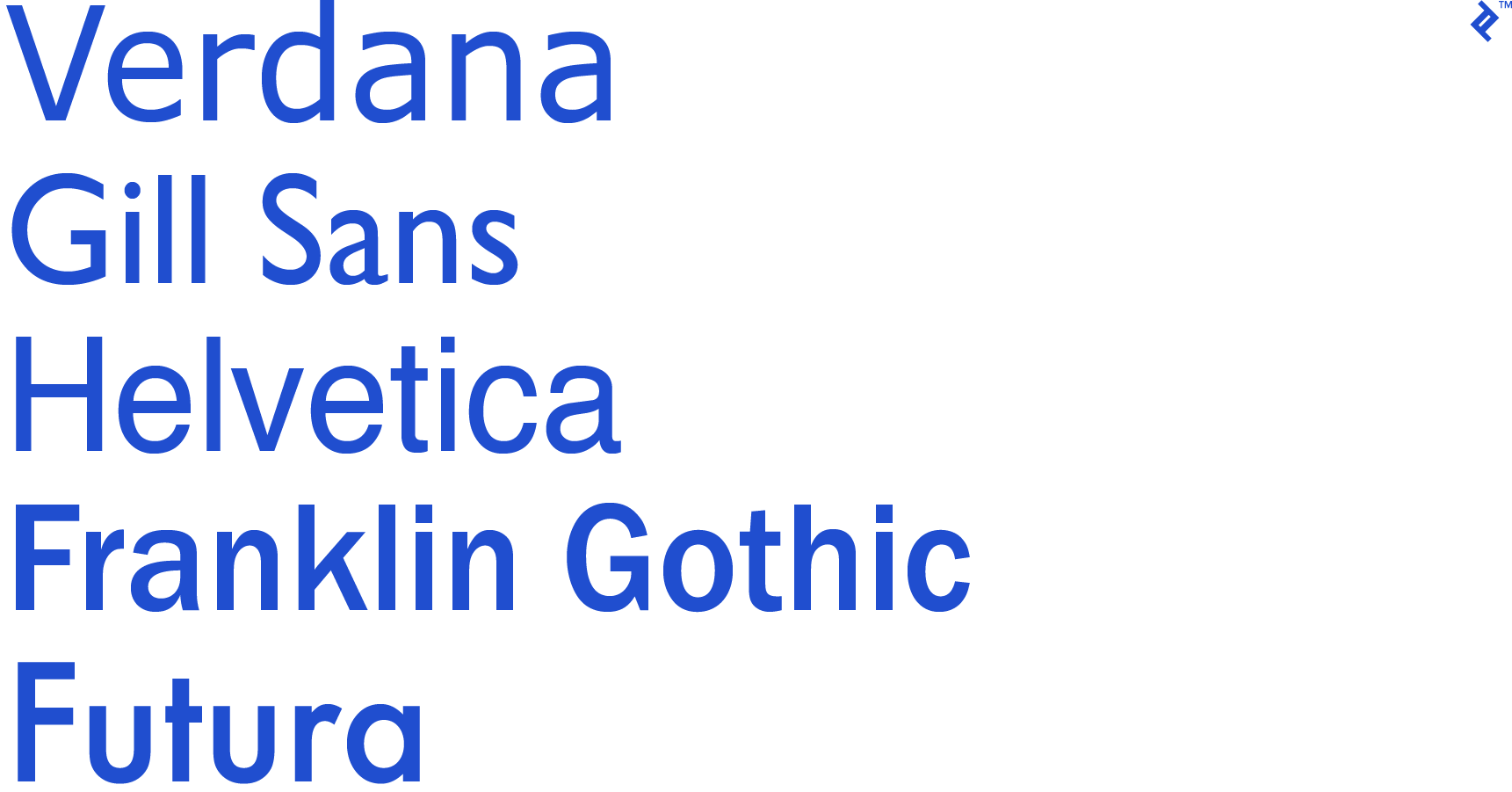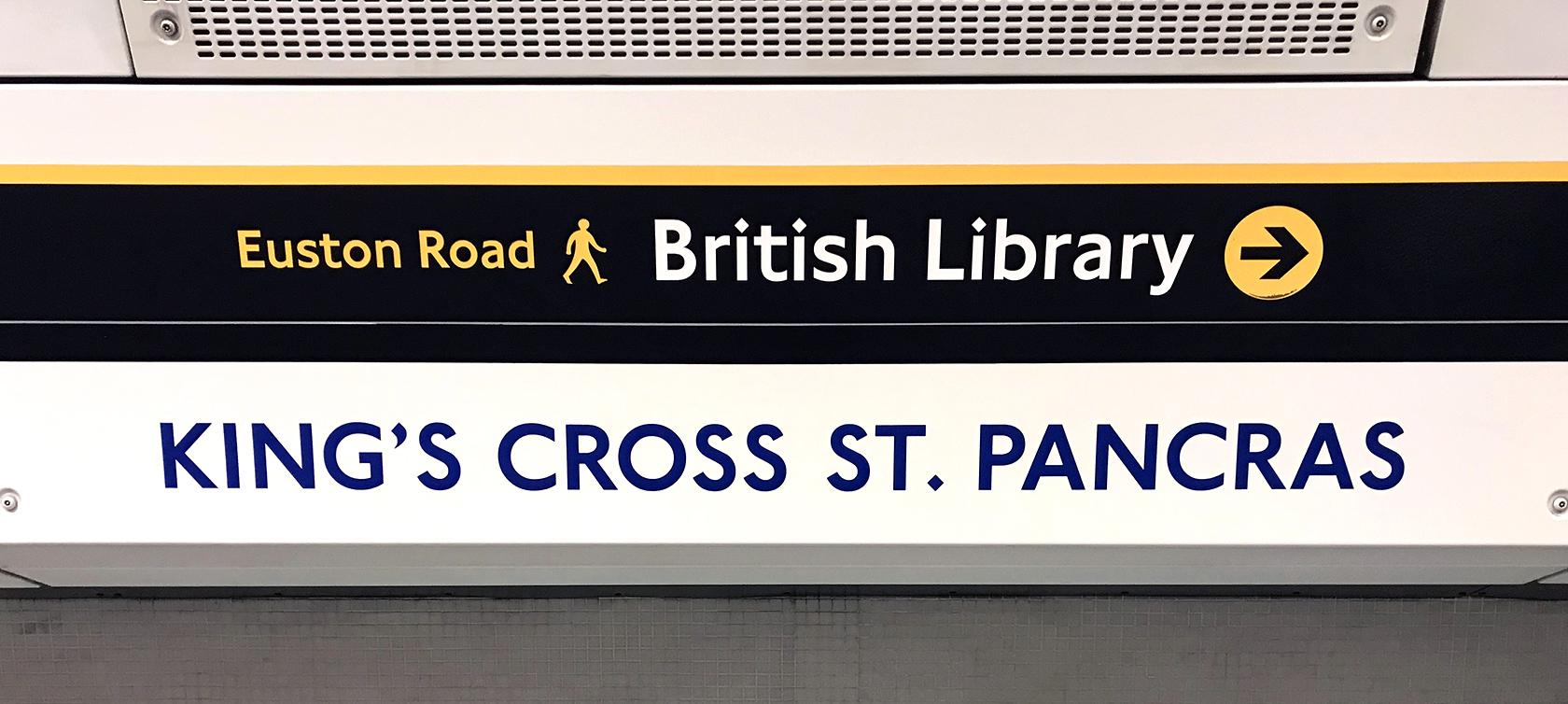
Estilos de Tipografía para la Web y Diseño Editorial e Impreso
Independientemente de la disciplina de diseño en la que estés trabajando, ya sea el diseño visual, UX o los tipos de tipografía tradicionales, son elementos esenciales de casi todo el diseño que se produce.
La gran mayoría de las personas son bombardeadas con tipos de letra desde el momento en que se despiertan por la mañana hasta el momento en que se van a la cama por la noche. Desde las aplicaciones en sus teléfonos hasta los productos de arreglo personal en sus baños hasta los letreros que ven en sus viajes diarios a la mañana, la tipografía está en todas partes. Pero ¿cuántas personas realmente notan los estilos tipográficos que rodean todos los días?
Incluso los diseñadores subestiman los estilos de tipografías y, a menudo, toman decisiones de tipografías basadas en una opinión vaga en lugar de una comprensión objetiva. ¿La mayoría de los diseñadores siquiera conocen los contextos industriales originales para los cuales se diseñaron varios tipos de letra? ¿Qué significan estos contextos e historias para determinar la legibilidad, el carácter apropiado y el uso de un tipo de letra dado? No importa en qué disciplina de diseño se esté trabajando, ya sea diseño visual o UX o tradicional diseño de impresión, los estilos de tipografía son elementos esenciales de prácticamente todo el diseño producido.
Algunos de los tipos de letra más influyentes actualmente en uso a menudo se pasan por alto a favor de diseños de tipografía únicos que son más nuevos en el mercado, y a veces con razón. Cada uno de los tipos de letra en este artículo tiene décadas, si no siglos, y fueron diseñados para diferentes contextos tecnológicos. Por lo tanto, se han creado muchas alternativas o actualizaciones desde que se introdujeron. Incluso algunas de las fuentes originalmente diseñadas para pantallas se han quedado obsoletas ya que las pantallas e impresoras se vuelven de mayor resolución y son capaces de mostrar formas más complejas con precisión.
Tipografías Serif
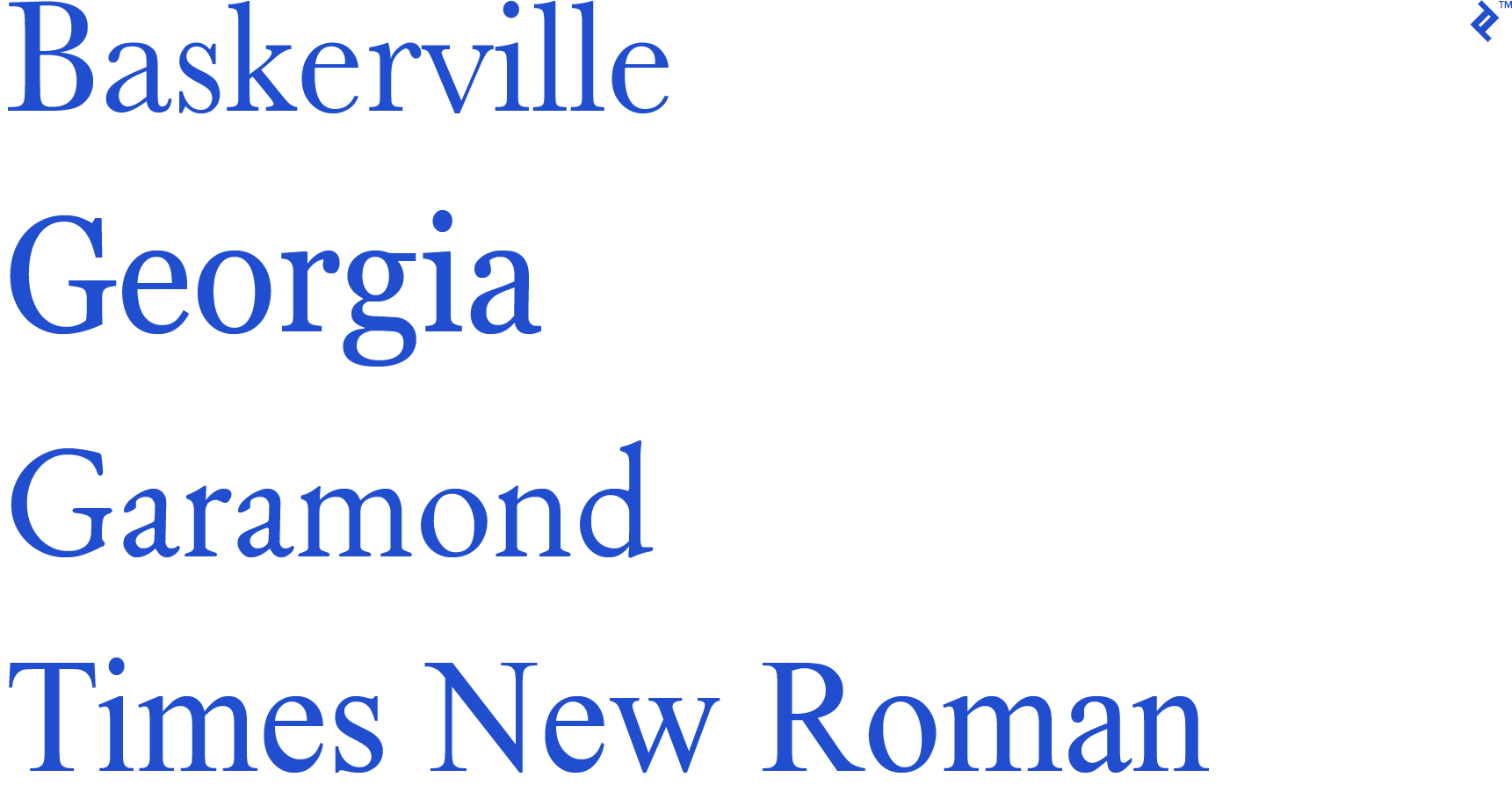
Comprender la diferencia entre los estilos de letra serif y sans-serif es una de las reglas de tipo más fundamentales. Para muchos esto puede ser obvio, pero el serif es el trazo dado al final de las principales líneas horizontales y verticales de un caracter. Hay muchas subclases dentro de serifs, incluyendo rayitas, cuñas y serifas de losas, que describen las cualidades visuales del serif.
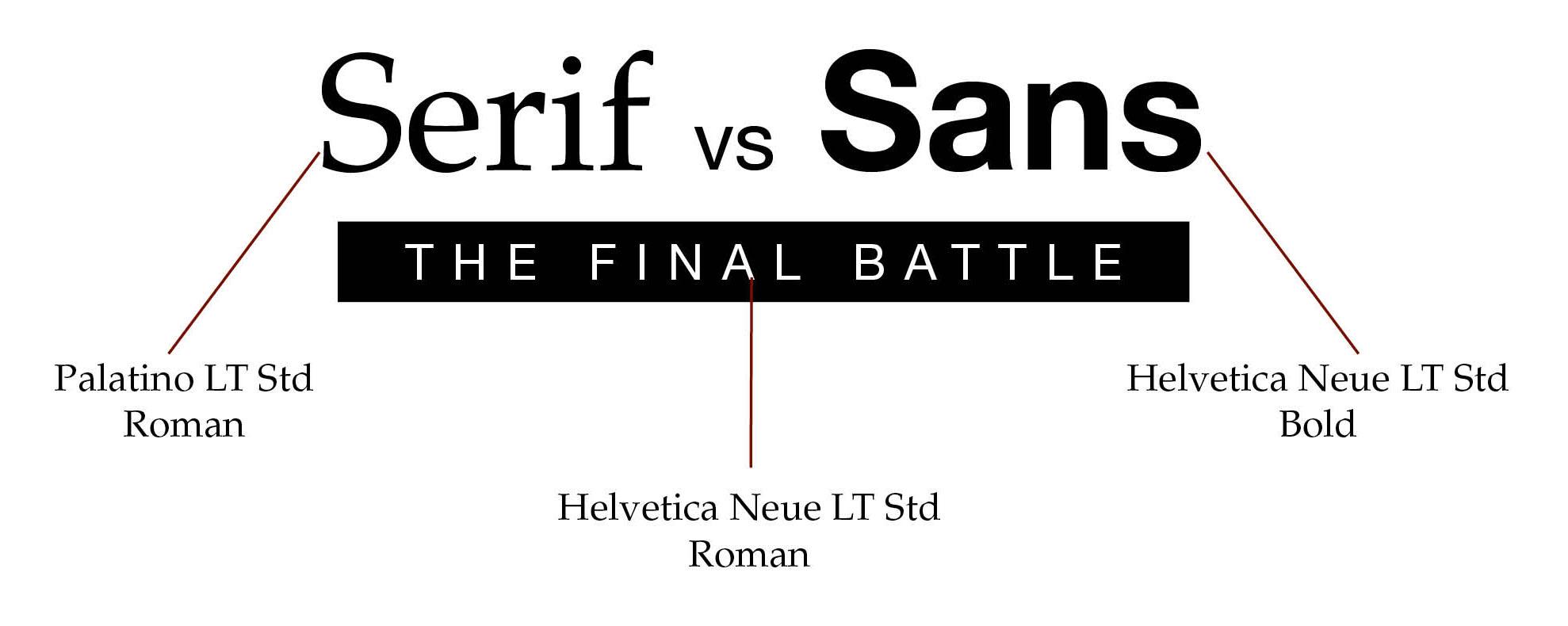
En general, las serifas tienen una historia más larga que las san serifs, ya que fueron las primeras tipografías usadas para imprimir libros después de la invención de Gutenberg Press. Esencialmente, las serifas permiten una lectura más cómoda en detalle, ya que las serifas guían el ojo suavemente de un personaje a otro, por lo que el serif es ideal para trabajos impresos largos. Debido a esto, las serifas aún son generalmente la fuente de referencia para trabajos impresos, como libros o informes, aunque no es una regla absoluta. Cada tipo de letra tiene sus propias cualidades específicas, y hay algunos tipos de letra serif que no son realmente adecuados para grandes fragmentos de texto corporal (y algunos tipos de letra sans-serif que son perfectamente legibles y legibles para trabajos largos).
Baskerville
Baskerville es una de las serifas clásicas que ha resistido la prueba del tiempo y todavía se usa ampliamente hoy en día. Baskerville fue diseñada en un período de transición entre las primeras caras tipográficas (Bodoni y Didot) y los tipos de letra de los siglos XIX y XX por venir. Baskerville ha tenido éxito debido a sus formas de letras de alto contraste.
El diseñador, John Baskerville, era un perfeccionista intenso y creó una fuente con hermosos detalles. El tipo de letra solo se puede imprimir en sus propias máquinas para garantizar que las formas de letras se transfieran correctamente a la página. Esta historia es significativa, ya que Baskerville se ha adaptado a los diversos medios en los que trabajamos hoy. Los detalles incorporados en cada forma de letra hacen que Baskerville no sea adecuado para medios de baja resolución, incluidas pantallas de baja resolución o impresoras defectuosas. Dicho esto, cuando Baskerville tiene la oportunidad de expresar su calidad, es una excelente tipografía serif.
Un buen ejemplo de una tipografía digital moderna en la que Baskerville ha influenciado mucho es la tipografía que Amazon ha encargado para Kindle, Bookerly. Si estás buscando una alternativa a Baskerville que mantenga su riqueza de 200 años mientras se actualiza para ser legible en la pantalla, Bookerly podría ser una buena solución. Otras alternativas incluyen Sra. Eaves y Plantin.
Times New Roman
Times New Roman, al igual que muchas fuentes ampliamente utilizadas desde hace un tiempo, es una tipografía polarizante que es amada por muchos pero también es detestada por algunos. A menudo, lo que las personas aman u odian sobre TNR es lo mismo: su neutralidad apática.
Matthew Butterick escribe “Times New Roman no es una elección de letra, sino la ausencia de una elección de fuente, como la negrura del espacio profundo no es un color. Mirar Times New Roman es contemplar el vacío”. Times New Roman se siente tan claro en gran parte debido a su abrumadora ubicuidad como resultado de su exposición del periódico para el que fue diseñado, el Times of London.
Cuando busques un tipo de letra para emparejar con una biblioteca de tipos existente para un uso más general en proyectos, concéntrate en elegir fuentes con características similares. Esto significa considerar todas las cualidades de las mayúsculas y minúsculas, x-alturas y geometría formal. Los sitios como Typewolf pueden ser muy valiosos para encontrar fuentes que se vinculen con las opciones existentes ya disponibles (así como también grandes alternativas para aquellos momentos en que un cliente dice que quiere algo “como” Helvetica pero definitivamente no Helvética).